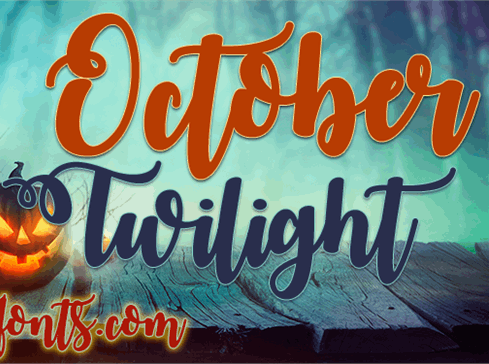
October Twilight Font – Download Grátis
A mistério do outono cai sobre as ruas brasileiras com a delicadeza de uma carta escrita à mão. A Misti’s Fonts apresenta-nos ‘October Twilight Font’, um encantador conjunto de letras em estilo escreva, perfeito para aqueles que desejam dar um toque pessoal e suave a suas criações digitais. Este font é uma janela que nos permite ver o dia se aproximando do final, com seu tom acolhedor e suavemente iluminado pelo último resplendor de luz do sol. É ideal para textos em seus trabalhos gráficos, seja um blog pessoal ou até mesmo uma página da web, trazendo um ar natural e autêntico a qualquer projeto. Sua elegância torna-o perfeito para o uso em design editorial, websites personalizados ou editoriais de blogs, proporcionando um toque único e sofisticado. Numa época do ano onde a natureza se prepara para descansar na quietude da noite, ‘October Twilight Font’ é uma font que captura esses sentimentos com beleza simples e inspiradora.